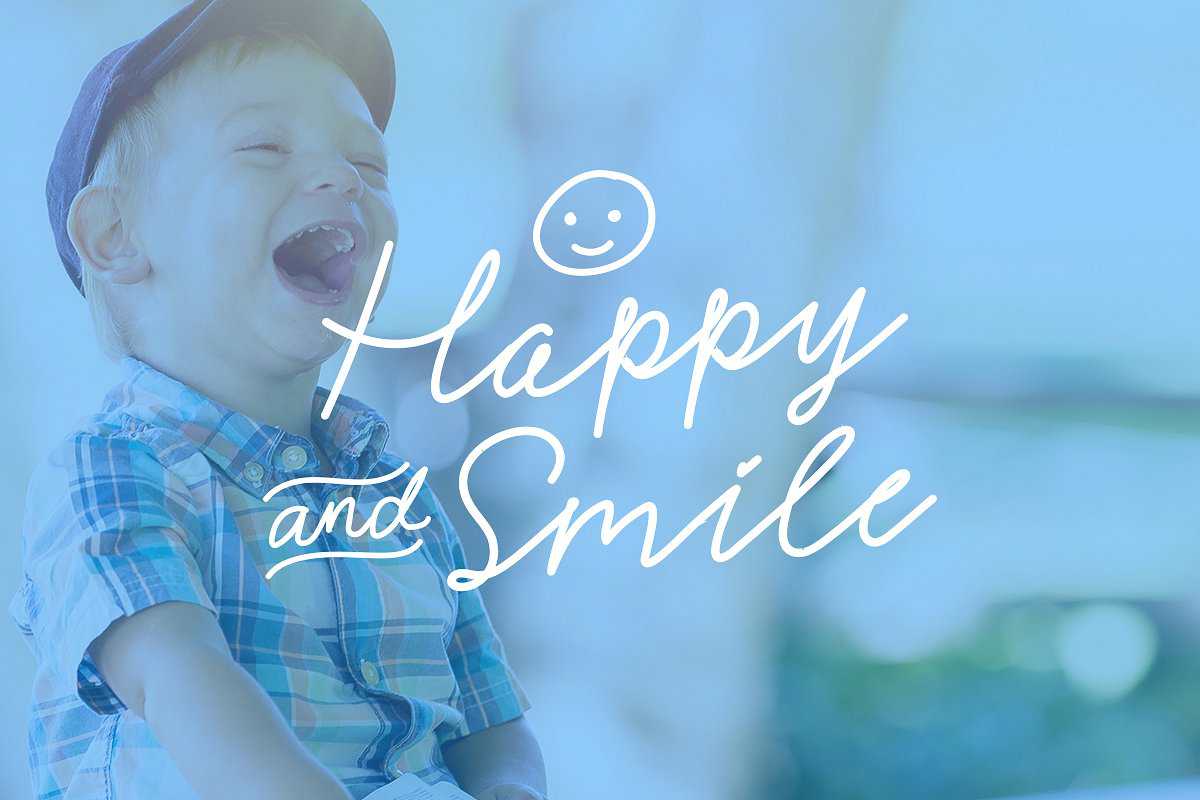
受手工手写签名的启发,这款字体充分体现了原始签名样式的感觉。这款字体有许多特点,包括符号和标点符号、风格选择、涂鸦、流行语、涂鸦图标、,还支持多语言字符。它还包括Signerella Sans FontTypes作为与Signerella脚本字体完全匹配的补充字体。您可以在Review中查看完整的字形。灵感来自手动手写签名,此字体充分体现了原始签名样式的感觉。此字体有许多特征,包括符号和标点符号、风格选择、涂鸦、流行语、涂鸦图标、,还支持多语言字符。它还包括Signerella Sans FontTypes作为与Signerella脚本字体完全匹配的补充字体。您可以在评论中查看完整的字形。